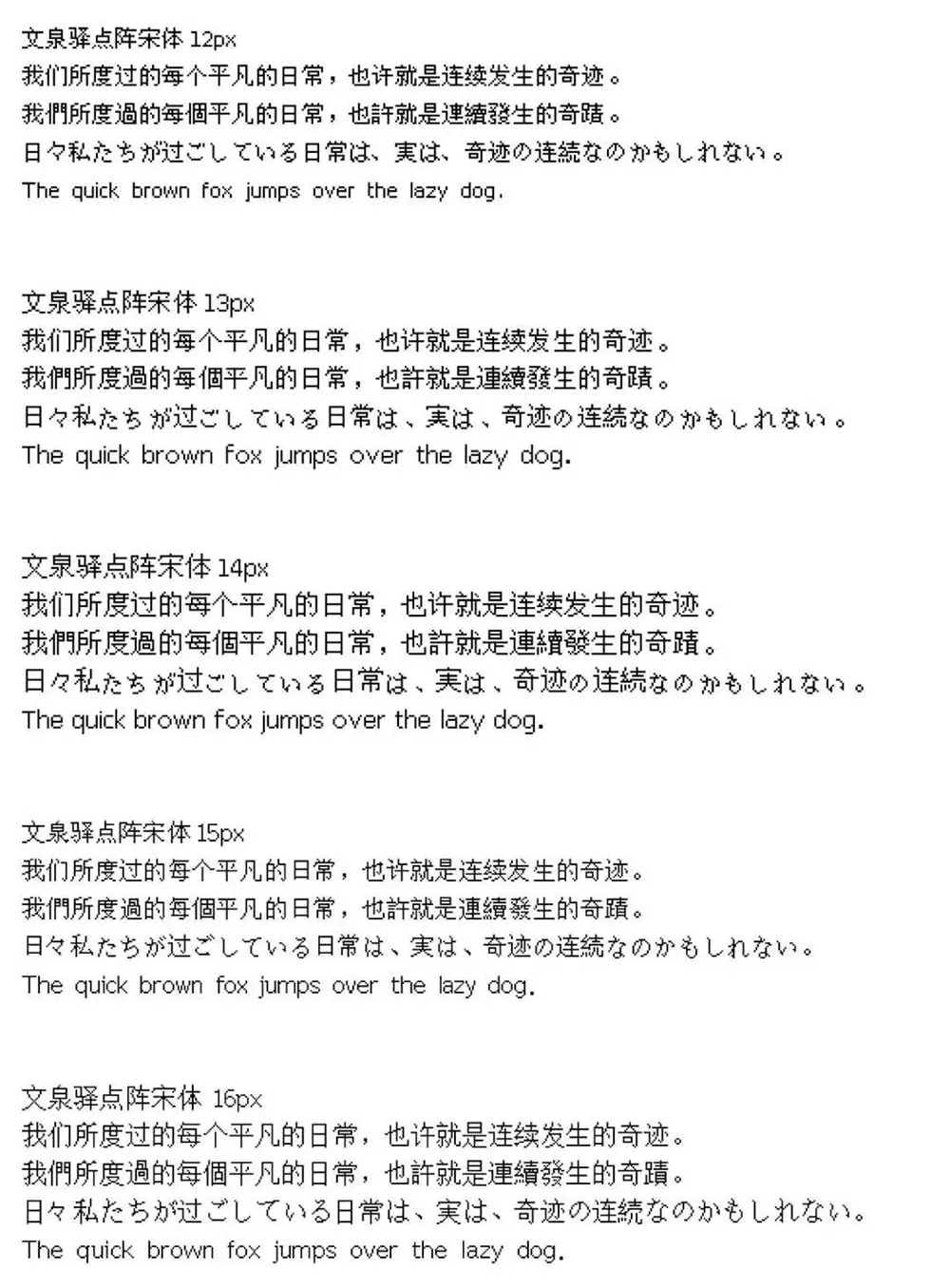
文泉驛點陣宋體是一個"自由中文字體"。該字體包含了所有常用簡體中文、繁體中文,日文及韓文所需要的漢字(最新版本包含超過27842個漢字,完整覆蓋GB2312/Big5/GBK/GB18030標準字符集)。該字體同時還包含了英文、日文、韓文和其他多種語言符號。該點陣字體包含五個屏幕常用字號(9pt-12pt),逾21萬漢字點陣,這些點陣都經過參與者和組織者的精心設計和調整,手工優化後的漢字點陣顯示清晰銳利,特別易於屏幕閱讀使用。
此為娛樂部以文泉驛點陣宋體 v1.0.0-RC1 的 PCF 字體制作的 TTF 版字體。希望可以給中文的點陣字體和像素字體增加一個新的選擇。